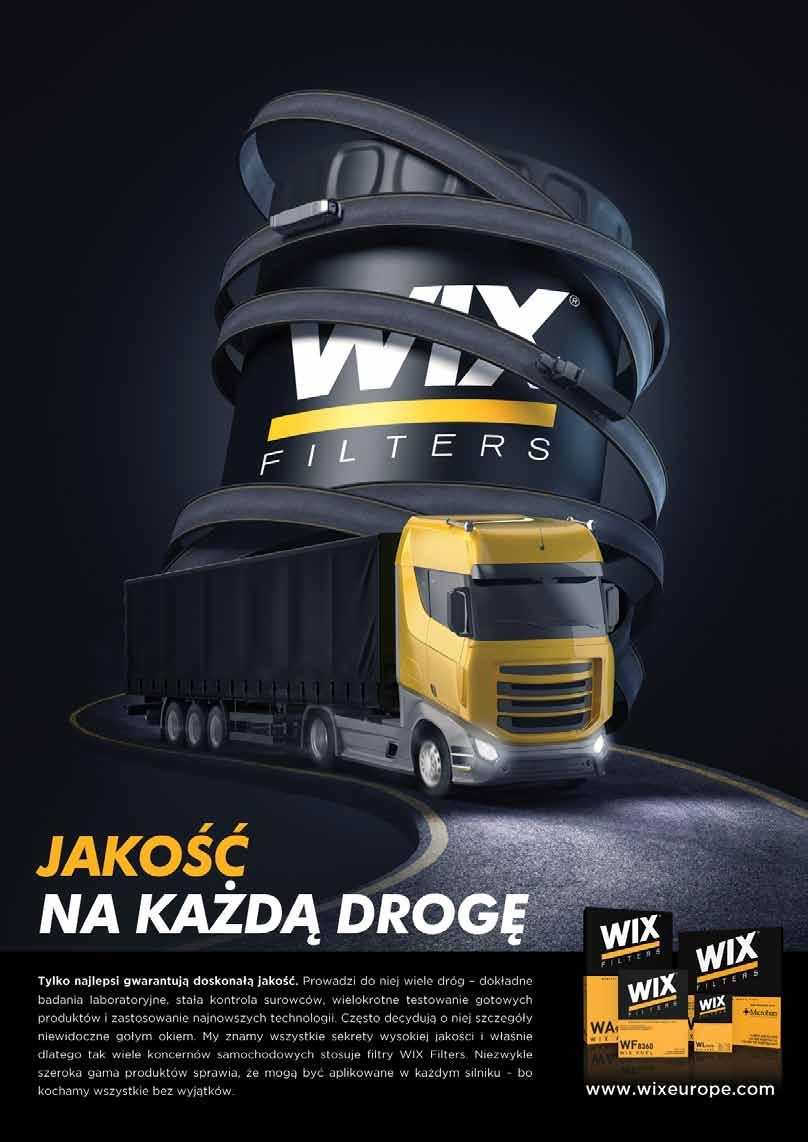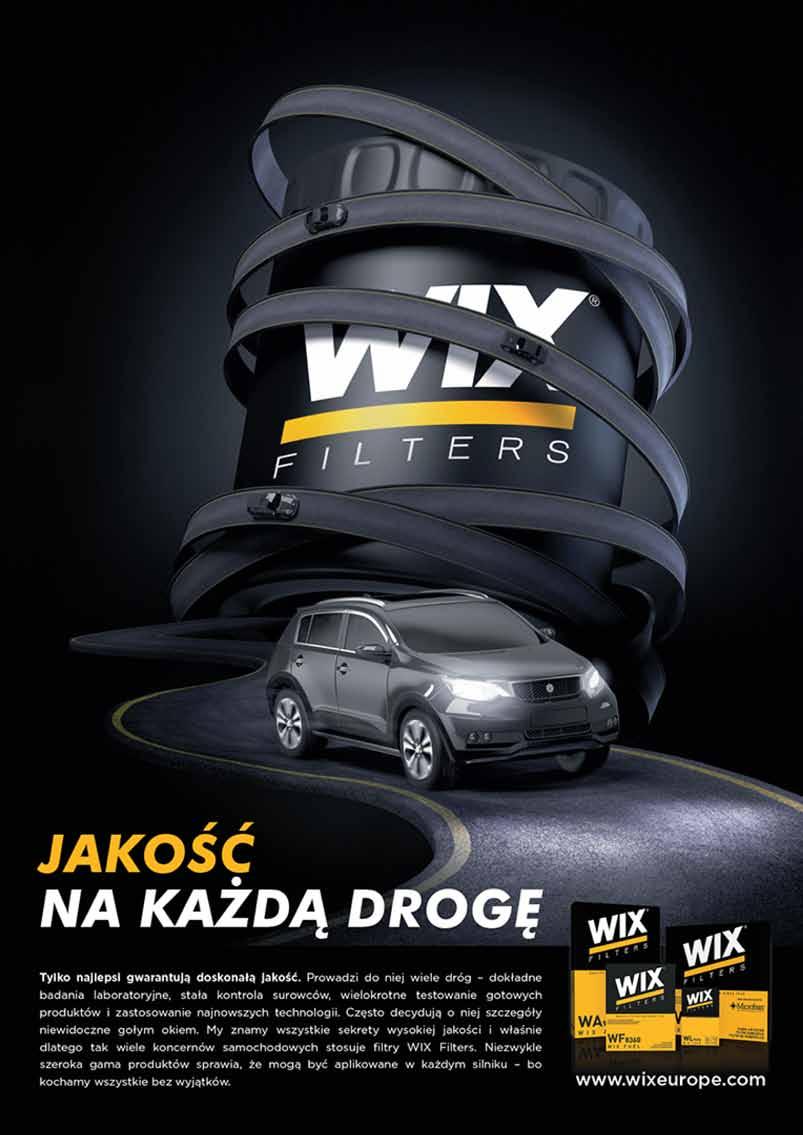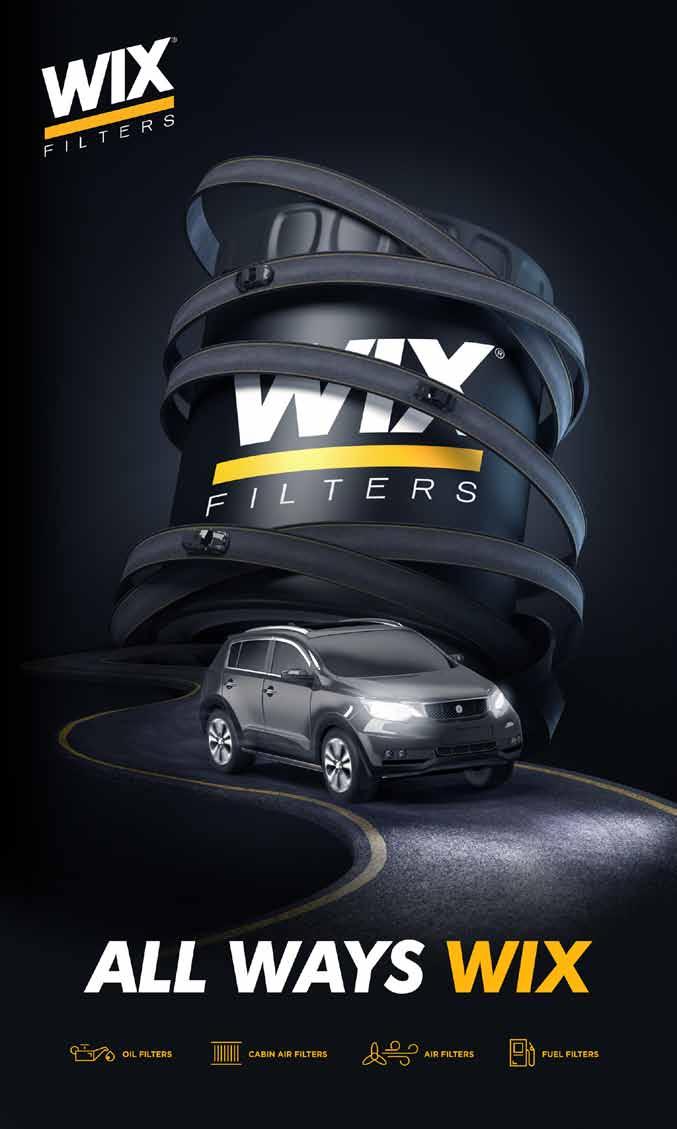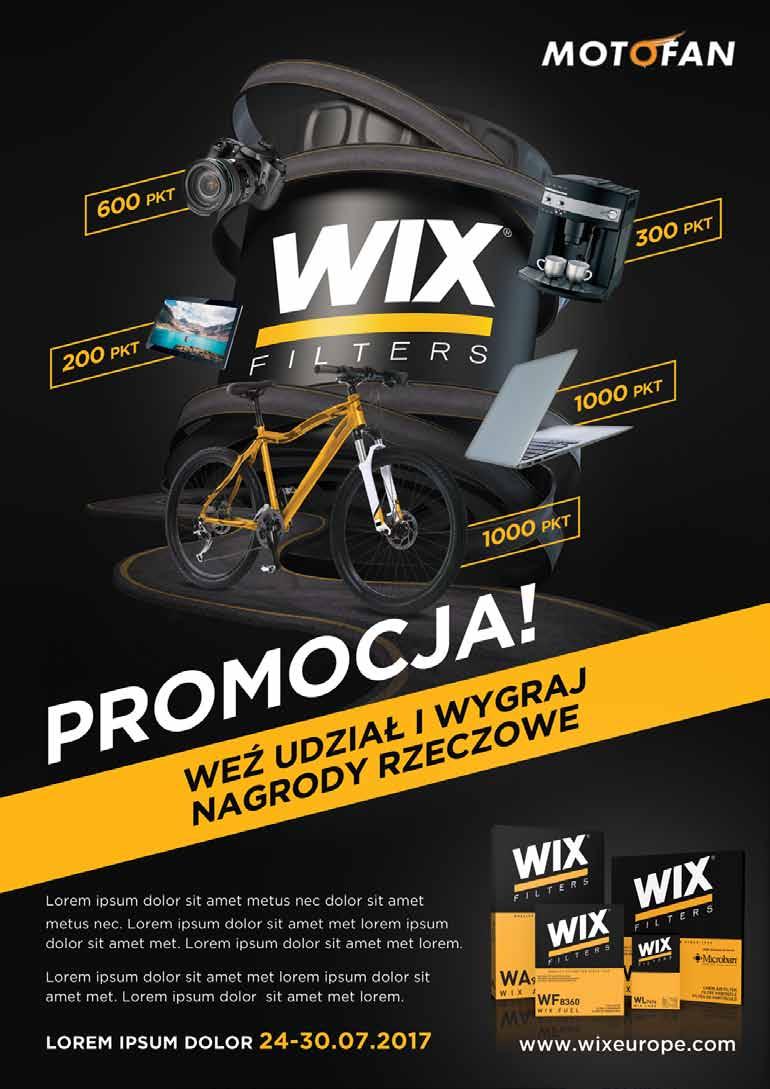
3 LOGO X X X X X WERSJA PODSTAWOWA Logo jest podstawowym elementem komunikacji wizualnej WIX Filters. Stosowanie go według określonych zasad pozwala budować spójny wizerunek marki. POLE OCHRONNE Przy stosowaniu logo należy zachowywać pole ochronne. Jest ono równe odległości od prawego górnego rogu żółtej belki do podstawy litery S. W tym obszarze nie należy umieszczać żadnych napisów ani grafik. MINIMALNA WIELKOŚĆ LOGO: 1,3 CM 3
4 LOGO WERSJE LOGO Podstawowa Jeden kolor - czarny Na czarnym tle Jeden kolor - biały NIEWŁAŚCIWE STOSOWANIE LOGO Stosując logo WIX Filters nie powinno się: - Zmieniać kolorystyki na inną niż określona w brandbooku - Modyfikować jego elementów - Dodawać cieni, obrysów i innych efektów - Umieszczać na tłach zbliżonych do koloru z logo lub wielokolorowych - Zmieniać kątu nachylenia (14 ) 4
5 LOGO WE LOVE ENGINES NIEWŁAŚCIWE STOSOWANIE LOGO Do logo WLE można dodać żółty pasek z prawej strony. Mogą się na nim znaleźć dodatkowe teksty. Stosując logo WIX Filters We love engines nie powinno się: - Zmieniać kolorystyki - Modyfikować jego elementów - Dodawać cieni, obrysów i innych efektów - Umieszczać na tłach zbliżonych do koloru z logo lub wielokolorowych - Obracać znaku - Przesuwać napisów na żółtych belkach 5
6 LOGO GLOBAL COVERAGE I WIX INSTITUTE LOGO WIX FILTERS GLOBAL COVERAGE To logo jest używane w kontekście WIX International. Pojawia się ono na wszystkich opakowaniach WIX Filters. LOGO WIX FILTERS INSTITUTE Jest to logo programu doszkalającego dla mechaników. 6
7 KOLORY PODSTAWOWE KOLORY WIX FILTERS Dla zachowania spójności marki, ważne jest odpowiednie używanie kolorów. W tabelce obok znajdują się wytyczne na temat reprodukcji kolorów WIX Filters w różnych systemach barwnych. WYJĄTEK W PRZYPADKU DRUKU NA NIEPOWLEKANYM PAPIERZE W przypadku druku koloru żółtego na niepowlekanym papierze należy zastosować kolor dodatkowy PMS 122U. Użycie PMS 1235C spowoduje uzyskanie koloru innego niż żólty kolor WIX Filters. DRUK NA NIEPOWLEKANYM PAPIERZE DRUK SPOT: 100% Black CMYK: 0/0/0/ 100 EKRANY RGB: 35/31/32 HEX: #231F20 HAFT DRUK SPOT: PMS 1235C CMYK: 0/33/97/0 EKRANY RGB: 255/182/15 HEX: #FFB60F HAFT SPOT: PMS 122U NIĆ SAKURA 2170 NIĆ SAKURA
8 FONT Gotham Bold AaBbCcDdEeFfGgHhIiJjKkLlMmNn OoPpQqRrSsTtUuVvWwXxYyZz Montserrat Bold AaBbCcDdEeFfGgHhIiJjKkLlMmNn OoPpQqRrSsTtUuVvWwXxYyZz Gotham Medium AaBbCcDdEeFfGgHhIiJjKkLlMmNn OoPpQqRrSsTtUuVvWwXxYyZz Montserrat Medium AaBbCcDdEeFfGgHhIiJjKkLlMmNn OoPpQqRrSsTtUuVvWwXxYyZz Gotham Book AaBbCcDdEeFfGgHhIiJjKkLlMmNn OoPpQqRrSsTtUuVvWwXxYyZz Montserrat Regular AaBbCcDdEeFfGgHhIiJjKkLlMmNn OoPpQqRrSsTtUuVvWwXxYyZz PODSTAWOWY ZAMIENNIK DO DIGITAL (GOOGLE FONTS) 8
9 FONT LOREM IPSUM DOLOR SIT AMET Lorem ipsum dolor sit amet, consectetur adipiscing elit. Proin nibh augue, suscipit a, scelerisque sed, lacinia in, mi. Cras vel lorem. Etiam pellentesque aliquet tellus. Phasellus pharetra nulla ac diam. Quisque semper justo at risus. Lorem ipsum dolor sit amet, consectetur adipiscing elit. Proin nibh augue, suscipit a, scelerisque sed, lacinia in, mi. Cras vel lorem. Etiam pellentesque aliquet tellus. Phasellus pharetra nulla ac diam. Quisque semper justo at risus. LOREM IPSUM DOLOR SIT AMET Lorem ipsum dolor sit amet, consectetur adipiscing elit. Proin nibh augue, suscipit a, scelerisque sed, lacinia in, mi. Cras vel lorem. Etiam pellentesque aliquet tellus. Phasellus pharetra nulla ac diam. Quisque semper justo at risus. ZASTOSOWANIE 9
10 FONT LOREM IPSUM ZASTOSOWANIE W WERSJI POCHYLONEJ PRZYKŁAD 10
11 IKONY FILTRY OLEJU FILTRY PALIWA FILTRY POWIETRZA FILTRY KABINOWE FILTRY SPECJALNE FILTRY OLEJU FILTRY PALIWA FILTRY POWIETRZA FILTRY KABINOWE FILTRY SPECJALNE FILTRY OLEJU FILTRY PALIWA FILTRY POWIETRZA FILTRY KABINOWE FILTRY SPECJALNE IKONY GRUP PRODUKTÓW WIX FILTERS Ikony te mogą być wykorzystywane w materiałach reklamowych. 11
12 IKONY IKONY DLA PRODUKTÓW HEAVY DUTY 12
13 IKONY PRZYKŁADY ZASTOSOWANIA IKON 13
14 KAMPANIA 2017 HASŁO KAMPANII NIEWŁAŚCIWE UŻYCIE Hasło stosujemy w jednej linii, nie łamiemy tekstu. 14
15 KEY VISUALS AUTOMOTIVE TRUCK 15
16 KEY VISUALS AGRI MARINE WIX RACING 16
17 WYTYCZNE DO TWORZENIA LAYOUTÓW KV LOGOTYP TEKST PRODUKTY GOTOWY LAYOUT LUB LUB INNY LOREM IPSUM DOLOR SIT AMET Lorem ipsum dolor sit amet, consectetur adipiscing elit. Proin nibh augue, suscipit a, scelerisque sed, lacinia in, mi. Cras vel lorem. Etiam pellentesque aliquet tellus. Phasellus pharetra nulla ac diam. Quisque semper justo at risus. UWAGI: UWAGI: UWAGI: W przypadku użycia KV z filtrem, na którym widnieje logotyp WIX Filters, nie musimy dodatkowo używać samego logotypu na layoucie. Logotyp WIX Filters staramy się umieszczać w prawym lub lewym górnym rogu. Nie dotyczy to logotypu We Love Engines. Na layoucie powinien znajdować się jeden główny headline. Packshoty umieszczamy w prawym lub lewym dolnym rogu. Należy zwrócić uwagę aby opakowania odcinały się od ciemnego lub żółtego tła. Powinien im zawsze towarzyszyć adres www: 17
18 PRZYKŁADY LAYOUTÓW 18
19 PLAKATY AUTOMOTIVE 19
20 PRASA 20
21 ROLL-UP GENERYCZNY ROLL-UP DLA PROXITECH (FRANCJA) 21
22 ULOTKI Miejsce na wstawienie logotypu partnera biznesowego. 2 WERSJE ULOTEK DLA PROMOCJI Z PARTNERAMI BIZNESOWYMI 22